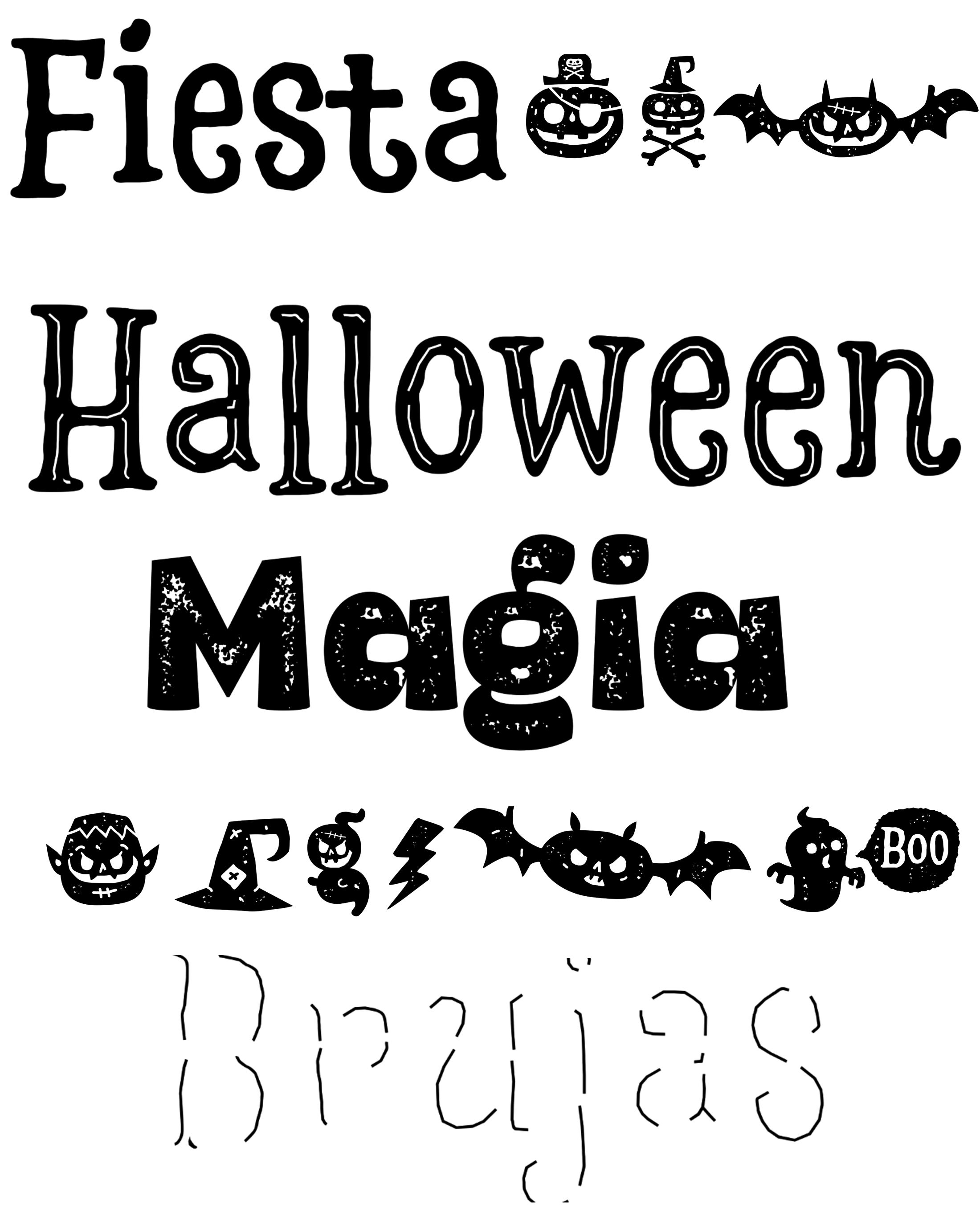
Hatter Halloween
| Descripción | Hatter Halloween, es una extensión de After, que incluye ligaduras, Extrude, Swash, Layers y contiene divertidos Dingbats para fiestas de Halloween o sobre temas de terror. |
| Familia(s) | Hatter Halloween Regular, Hatter Halloween Fear, Hatter Halloween Danger, Hatter Halloween Ding Rough, Hatter Halloween Ding Extrude, Hatter Halloween Extrude One, Hatter Halloween Dingbats, Hatter Halloween Dingbats Two, Hatter Halloween Dingbats Dirt, Hatter Halloween Dingbats Dirt 2 |
| Estilos | 12 |